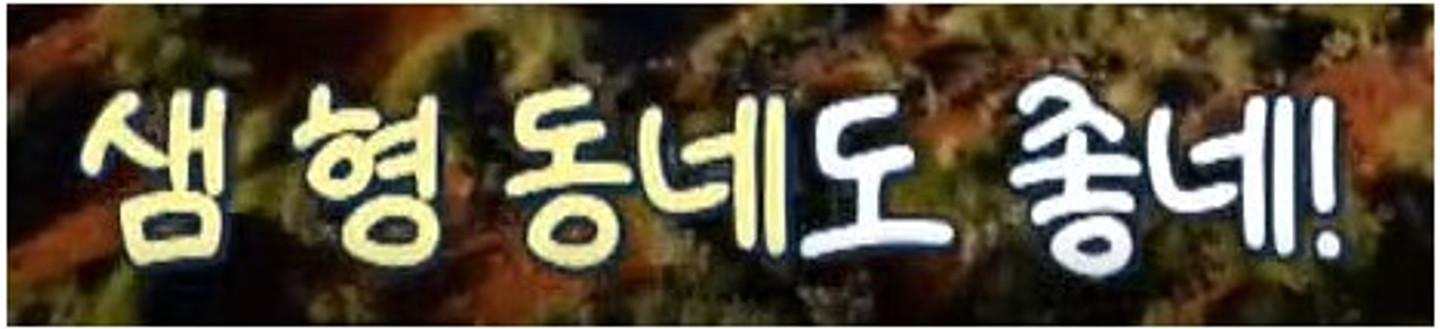
ㅏㅑㅓㅕ 계열의 세로형 모음이 있는 글자의 초성에 ㄱ이 올 경우 특유의 생김새가 있는 필기체 형태의 글씨체입니다. 2011년쯤에 쓰여진 것으로 추정되는 문서의 일부입니다. 개인적인 생각으로는 한글 프로그램의 기본 서체가 아닌가 하여 찾아보았으나 찾지 못했습니다. 찾아주시는 분께는 정말 감사드립니다.
기본 텍스트가 궁금합니다!! 영상 원본 링크는 이렇게됩니다. https://www.youtube.com/watch?v=S-mYEe_HAQg
노란 폰트와 하얀 폰트 둘 다 궁금합니다!ㅠㅜ 하얀 폰트는 기역(ㄱ)이 안 꺾이고 세로획이 더 긴 것이 특징입니당 +답변 감사합니다!! 🥰